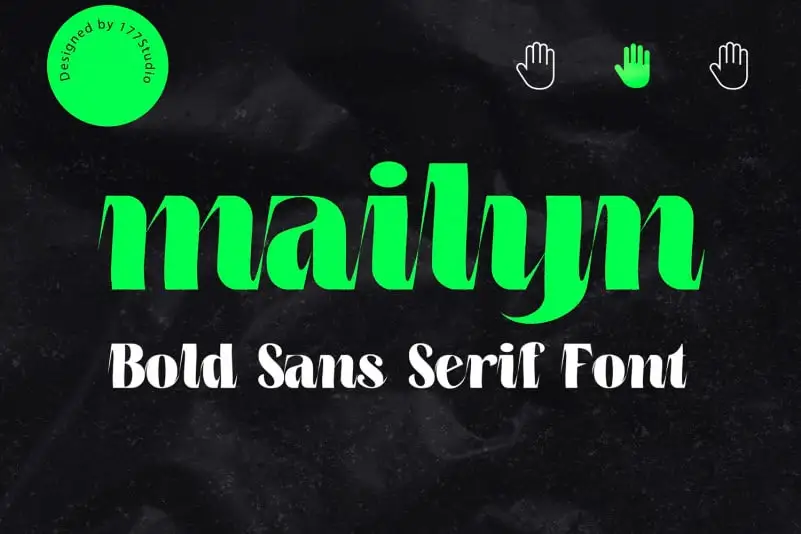
Mailyn Display Font – Download Grátis
A Mailyn Display Font é uma elegante tipografia sans serif que combina sofisticação com modernidade. Com seu estilo de sans-serif forte que transmite a sensação dos caracteres maiúsculos, ela oferece um equilíbrio perfeito entre letras grandes e menores. Suas casas altas extensas proporcionam uma grande variedade para designers criarem opções flexíveis e personalizadas para diversos projetos. É perfeita tanto para headlines que exigem atenção imediata, como logos que precisam de um estilo sólido e moderno, ou até mesmo para aplicar em t-shirts, embalagens e posters. Este font é versátil e funcional, adequado a uma ampla gama de projetos, tornando-o uma opção ideal para designers buscando estilizar suas criações de maneira eficiente e sofisticada.